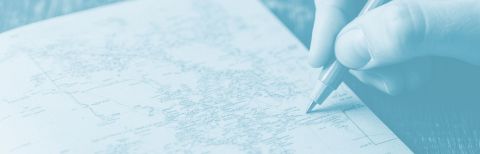
Handschrift und meine kleinen Abenteuer
Mit der Nutzung digitaler Technologien verschieben sich grundlegende Merkmale gesellschaftlicher Bildung. Jedoch sind wir erst dann vollkommen, wenn Menschen die Fähigkeit zum handschriftlichen Ausdruck kultivieren. Denn handschriftliches Schreiben zählt zum kulturellen Bildungskapital. Laut Umberto Eco, dem bekannten Schriftsteller und ehemaligen Professor für Semiotik, lehrt die Kunst des Handschreibens uns, die Hände zu kontrollieren, und sie schult die Hand-Auge-Koordination. Das Schreiben mit der Hand verpflichtet uns, den Satz mental zu verfassen, bevor wir ihn niederschreiben, so Eco.
Hier leistet die Stiftung Handschrift einen wichtigen Beitrag zur Kultivierung einer Kompetenz, die vom Verschwinden bedroht ist.
Vom beruflichen Alltag nehme ich mir ab und zu eine kleine Auszeit und gehe wandern. Das Zusammenspiel von Wandern, Abenteuerlust und Natur kombiniere ich stets mit dem Besuch einer interessanten Ausstellung. Die Planung meiner Wanderrouten und selbst die Anfahrt tätige ich übrigens in handschriftlicher Skizzenform. Im letzten Jahr war ich zur Herbstzeit im Paderborner Land unterwegs.
Der Zufall wollte es, dass ich die Sonderausstellung Corvey und das Erbe der Antike. Kaiser, Klöster und Kulturtransfer im Mittelalter im Diözesanmuseum Paderborn besuchen durfte.
Das mittelalterliche Kloster Corvey gilt als Hort des Wissens, bewahrte wichtige christliche Texte, aber auch Schriften antiker Autoren wie Vergil, Livius oder Ovid. Viele dieser Schriften sind uns heute nur bekannt, weil sie Mönche im Mittelalter kopierten. Die handschriftlichen Kopien sehen zum Teil heute noch aus, als wären sie erst gestern niedergeschrieben worden. Die Ausstellung legte Zeugnis ab von antiken Kulturtechniken der Handschrift, der Illustration und einer Erdung für das Schöne.
Dieses kleine museale Abenteuer hat mich begeistert und mir die Bedeutung der Handschrift nochmal vor Augen geführt. Ich bin mir sicher, Eco hätte seine wahre Freude an der Ausstellung und den handschriftlichen Exponaten des Mittelalters gehabt.